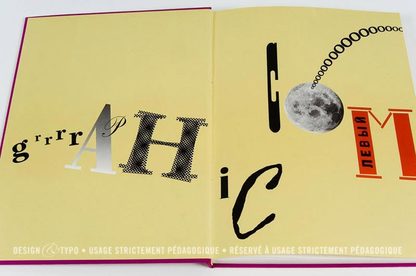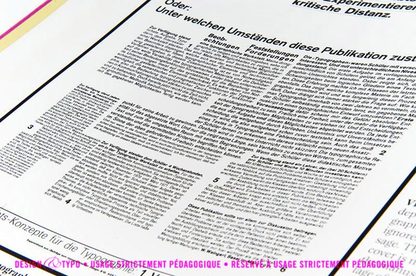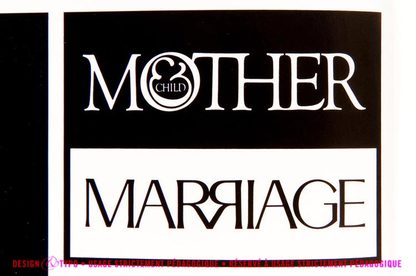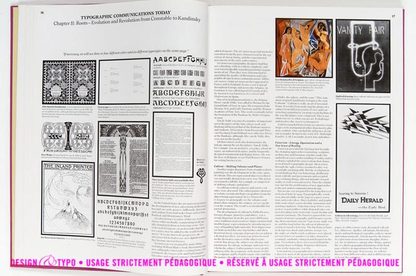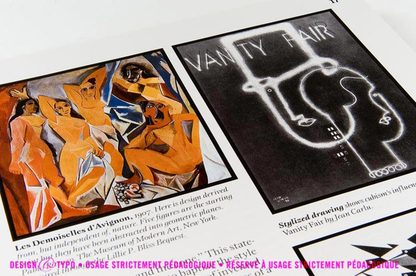
Lorsque Edward M.Gottschall s’attaque à «son histoire» de la Typographie et des Arts Graphiques, il se trouve rapidement confronté à plusieurs écueils, dont pour n’en citer que quelques uns:
• définir son périmètre ou corpus
• le volume (format et pagination) qu’il compte y consacrer
• le découpage
• les illustrations
• une difficulté majeure: le marketing de l’édition
Et je commence par la fin. Gottschall était n’oblions pas l’un des trois fondateurs d’ITC. Lubalin et Burns en tête. Il était un peu l’ingénieur, le financier, le logisticien de cette entreprise d’édition de caractères qui connut un des succès les plus fulgurant dans le monde extrêmement fermé des Fondeurs de caractères. La raison en fut comme je l’ai déjà expliqué dans mes articles consacrés à Herb Lubalin, que pour la première fois dans l’histoire de la typographie, la création des polices était déconnecté de l’industrie des fabricants de supports de composition.
ITC, d’emblée se positionnait comme un éditeur de caractères et non comme un fabricant. Ce qui lui vaut aujourd’hui encore d’avoir conservé une modernité structurelle puisque son modèle économique n’a souffert d’aucun vieillissement depuis près de 36 ans, tout de même un record de longévité dans un monde des industries graphiques qui connut des bouleversements saisissants.
Mais lorsqu’il s’attaque à l’écriture de cet ouvrage Gottschall est confronté à un frein immense. Celui d’être d’emblée taxé d’écrire un livre à la gloire d’ITC. Une sorte d’autopromotion marketing qui viendrait s’ajouter aux nombreuses publications des Upper & Lower Case et catalogues divers que la firme distribuait gratuitement de par le monde. Et du coup s’est posé pour lui tout un tas de questions d’ordre éthique, financier, marketing et, et méthodologique.
Pour balayer les arguments des détracteurs il décida tout d’abord du corpus:
L’évolution croisé des trois domaines historiques :
• la forme des caractères depuis la fin du XIXe siècle, avec tout de même un chapître entier consacré à une classification très «américaine» des caractères,
• l’évolution des technologies de composition qui influent considérablement sur les formes typographiques ainsi que sur leur créativité
• l’évolution graphique de la mise en scène de la typographie au cours du XXe siècle en prenant pour point de départ la fin toujours du XIXe.
Et puisque problème d’éthique il y avait, et que Gottsschall n’était lié à aucune contrainte économique aucun frein financier parce qu’ITC nagait alors en plein succès faisant des profits plus que confortables, il décida de consacrer et l’espace nécessaire (no limit) pour le format (260×360 fermé) et le nombre de pages (voire de cahiers) qu’il fallait pour racconter «son» histoire de la Typographie.
Au total il publiera 250 pages tiré sur un simili chromomat ou job classique en 135 gramme.
Pour les connaisseurs il respectera jusqu’à la superposition des alignements typographiques des pages recto-verso pour éviter le moindre cafouillage due parfois à la transparence des papiers.
Pour ce qui est des illustrations, Gottschall prendra tel Kissinger l’avion à Kennedy Airport et fera au moins deux tours du monde pour aller à la pêche aux images. Il n’avait pas trop le temps Gottschall. Devait déjà avoir plus de soixante ans et, sans internet pour communiquer. Avec un crédit quasi illimité, et la nécessité de boucler le dossier en quelques mois pour pouvoir prendre sa retraite, il a engagé tous les moyens nécessaires à la collecte des illustrations.
Son premier chapître : Many Faces of Typographic Design n’est qu’une mise en bouche avant l’entrée véritable. Il y étale en long et large la prolifération typographique pointant à la fois l’ordre et la confusion qui alterne dans cet art (en parlant de la scénographie).
Seul clin d’œil à Herb Lubalin en ce début d’ouvrage…
Le deuxième chapître: évolution et révolution depuis Constable à Kandinsky.
Là nous entrons dans le vif du sujet puisqu’il fait un rapide retour en arrière sur l’histoire de l’art pour venir en fin de compte légitimer avec l’apparition de l’Art Nouveau (Mucha, Grasset, Will Bradley) l’introduction de la typographie dans les arts plastiques. Un peu léger tout de même, surtout après avoir lu l’introduction d’Alain Korkos à cette série de billets. Mais il fallait bien démarrer son ouvrage.
«L’Art Nouveau s’inspirait de boucoup d’influences: Les illustrations de livres de William Blake, la calligraphie Japonaise, les dessins incurvées de Van Gogh, les ornements Celtiques, le style rococo ainsi que les aplats colorés chers à Gauguin»…
Et il en arrive enfin à citer le Belge Henri Van de Velde qui fut appelé par le Grand Duc de Saxe en 1902 pour réorganiser l’institut des Arts Appliqués avec les Beaux Arts de Weimar. Sans doute anticipant ainsi sur la future fondation du Bauhaus par Walter Gropius.
Une composition futuriste de F.T.Marinetti, 1919.
Et il aborde la naissance du mouvement Dada avec l’écrivain hongrois Tristan Tzara qui à l’instar des artistes contemporains épprouvait la nécessité de déconstruire les canons de l’esthétique traditionnelle en réaction aux pesanteurs d’un monde ancien qui refuse la modernité.
à gauche Carlo Carrà (1914), à droite George Grosz, une couverture pour le magazine Der Blutige Ernst (1919).
1912, Duchamp (l’image est ici couché à 90° à gauche ;-), Nue descendant un escalier.
Kurt Schwitters, 1927, un projet d’alphabet phonétique.
1917, Calligrammes de Guillaume Appolinaire et à droite, 1923, Ilya Zdanevitch. 40 polices étaient au moins utilisés dans cette composition. (1 police à cette époque correspondait non seulement à un dessin mais aussi à un corps donné).
Wassily Kandinsky, 1934, huile et sable sur toile. Guggenheim, New-York.
Le Chapitre III s’intitule : L’ordre après le Chaos